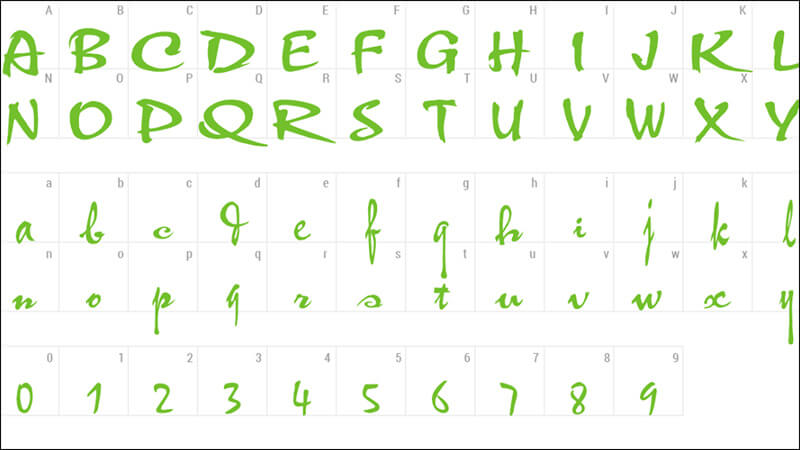
Tổng hợp các bộ download font chữ thư pháp phổ biến
Trước khi chọn font cho thiết kế, bạn nên tham khảo một số bộ font thư pháp phổ biến để xác định đúng phong cách mình cần. Có bộ font thiên về nét chữ truyền thống, có bộ lại pha trộn phong cách hiện đại để phù hợp với poster, banner hoặc các ấn phẩm quảng cáo.
Các font thư pháp thường mang nét chữ mềm mại, bay bổng và tạo cảm giác nghệ thuật rõ rệt. Đây là lý do nhiều designer ưu tiên download font chữ thư pháp khi thực hiện các thiết kế cần tạo cảm xúc hoặc mang màu sắc văn hóa.
| Font | Phong cách | Ứng dụng | Hỗ trợ tiếng Việt |
|---|---|---|---|
| Thư Pháp Thiên Ân | Calligraphy | Thiết kế Tết | Có |
| Font Ông Đồ | Thư pháp Việt | Câu đối, banner | Có |
| Font Xuân | Thư pháp hiện đại | Poster Tết | Có |
| Font Thư Pháp Việt Hóa | Calligraphy | Thiệp chúc mừng | Có |
05 đặc điểm nổi bật của font chữ thư pháp
Font thư pháp không chỉ đẹp về mặt hình thức mà còn có nhiều đặc điểm riêng khiến nó khác biệt hoàn toàn so với các font chữ phổ thông. Nếu hiểu rõ bản chất của loại font này, bạn sẽ dễ chọn đúng kiểu chữ phù hợp với mục tiêu thiết kế hơn.
Dưới đây là những điểm nổi bật thường thấy khi sử dụng download font chữ thư pháp trong thiết kế:
- Nét chữ bay bổng: các ký tự thường có độ uốn lượn cao, tạo cảm giác mềm mại và giàu tính nghệ thuật.
- Đường nét tự nhiên: nhiều font mô phỏng bút lông hoặc bút mực nên nhìn giống chữ viết tay truyền thống.
- Tạo cảm giác truyền thống: rất phù hợp với các thiết kế văn hóa, lễ hội hoặc ấn phẩm mang màu sắc Á Đông.
- Tăng tính thẩm mỹ: giúp phần tiêu đề và slogan nổi bật hơn nhiều so với font chữ thông thường.
- Phù hợp thiết kế nghệ thuật: thường được dùng trong poster, thiệp, banner, bao lì xì hoặc logo phong cách truyền thống.
Chính vì những đặc trưng này, download font chữ thư pháp không chỉ là lựa chọn về mặt thẩm mỹ mà còn là công cụ giúp định hình phong cách cho toàn bộ thiết kế.
Ứng dụng của font chữ thư pháp trong thiết kế
Font thư pháp không phải kiểu chữ dùng cho mọi tình huống, nhưng khi đặt đúng chỗ, nó có thể tạo ra hiệu quả thị giác rất mạnh. Loại font này đặc biệt phù hợp với các thiết kế cần truyền tải cảm giác trang trọng, truyền thống hoặc có tính nghệ thuật rõ rệt.
Trên thực tế, nhiều designer lựa chọn download font chữ thư pháp không chỉ để làm tiêu đề mà còn để tạo dấu ấn cho các chi tiết chính trong bố cục. Một số ứng dụng phổ biến của font thư pháp gồm:
- Thiết kế thiệp chúc mừng.
- Poster Tết hoặc banner sự kiện.
- Thiết kế câu đối thư pháp.
- Logo thương hiệu mang phong cách truyền thống.
- Thiết kế bao lì xì hoặc hộp quà Tết.
- Bìa sách, bìa album hoặc ấn phẩm nghệ thuật.
Nhờ phong cách chữ đặc biệt, việc download font chữ thư pháp giúp thiết kế dễ tạo được điểm nhấn thị giác và truyền tải đúng tinh thần của nội dung hơn so với các font chữ phổ thông.
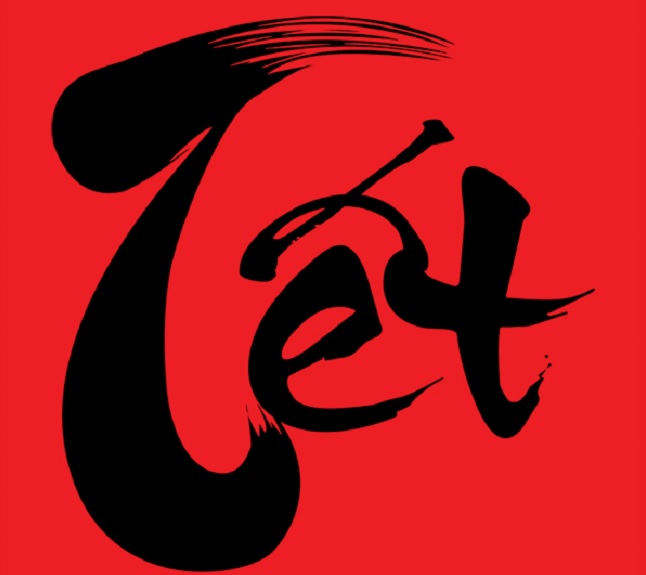
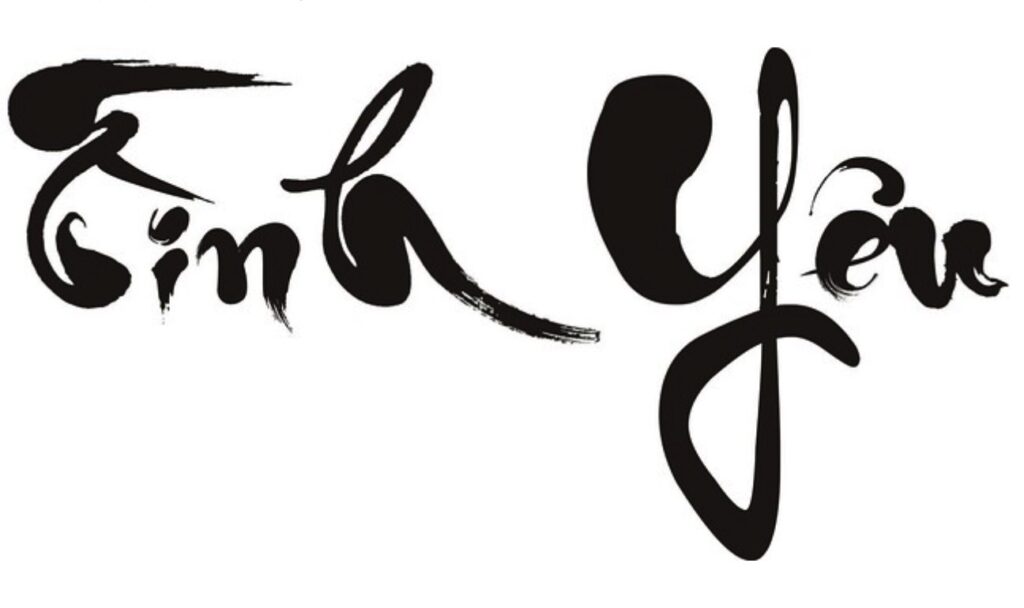
04 lỗi thường gặp khi download font chữ thư pháp
Dù các font thư pháp rất đẹp, nhưng không phải bộ font nào tải về cũng có thể dùng ngay. Nhiều người gặp lỗi khi cài đặt hoặc khi gõ tiếng Việt, đặc biệt là với những font lấy từ nguồn không rõ ràng hoặc chưa được Việt hóa đầy đủ.
Để tránh mất thời gian xử lý, bạn nên lưu ý một số lỗi phổ biến khi download font chữ thư pháp:
- Font không hỗ trợ tiếng Việt: chữ hiển thị sai dấu hoặc thiếu ký tự khi gõ nội dung có dấu.
- File font bị lỗi: tải về nhưng không cài đặt được hoặc phần mềm không nhận diện.
- Font quá rối: nhìn đẹp nhưng khi đưa vào thiết kế thực tế lại khó đọc, đặc biệt ở kích thước nhỏ.
- Không tương thích phần mềm: một số font hiển thị lỗi khi dùng trong Photoshop, Illustrator hoặc CorelDRAW.
Vì vậy, khi tải font chữ thư pháp, bạn nên ưu tiên các bộ font đã được kiểm tra trước về khả năng hiển thị và hỗ trợ tiếng Việt để tránh phát sinh lỗi không cần thiết trong quá trình thiết kế.
03 lưu ý khi sử dụng font thư pháp trong thiết kế
Font thư pháp có thể làm thiết kế đẹp hơn, nhưng nếu dùng không đúng cách thì bố cục lại rất dễ trở nên rối mắt. Đây là kiểu chữ thiên về cảm xúc và nghệ thuật, vì vậy cần đặt đúng vị trí để phát huy hiệu quả.
- Không dùng cho đoạn văn dài: font thư pháp phù hợp nhất với tiêu đề, slogan hoặc một số cụm từ cần nhấn mạnh.